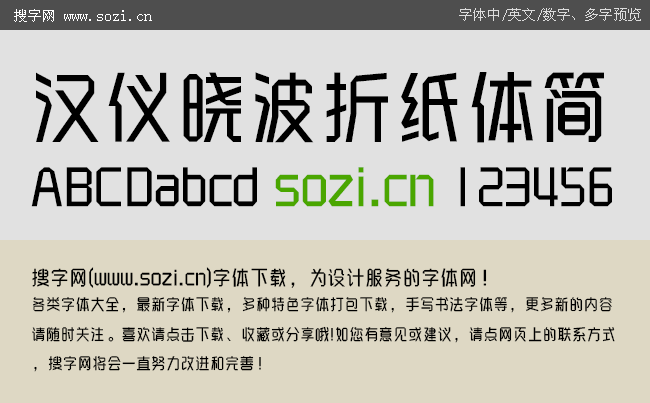
漢儀曉波折紙?bào)w簡手機(jī)字體包
搜字網(wǎng)給大家提供一款漢儀曉波折紙?bào)w簡手機(jī)字體包手機(jī)中文字體下載。本字體筆畫連接如同折紙,每個(gè)折角都處理成紙張折疊效果,設(shè)計(jì)師可以用它實(shí)現(xiàn)想要的拉伸和切割效果,折紙?bào)w會很好的視覺呈現(xiàn).瘦高的比例也使它在具有時(shí)尚高挑的現(xiàn)代感同時(shí),又有很強(qiáng)設(shè)計(jì)感和趣味性。喜歡的朋友趕快下載吧。